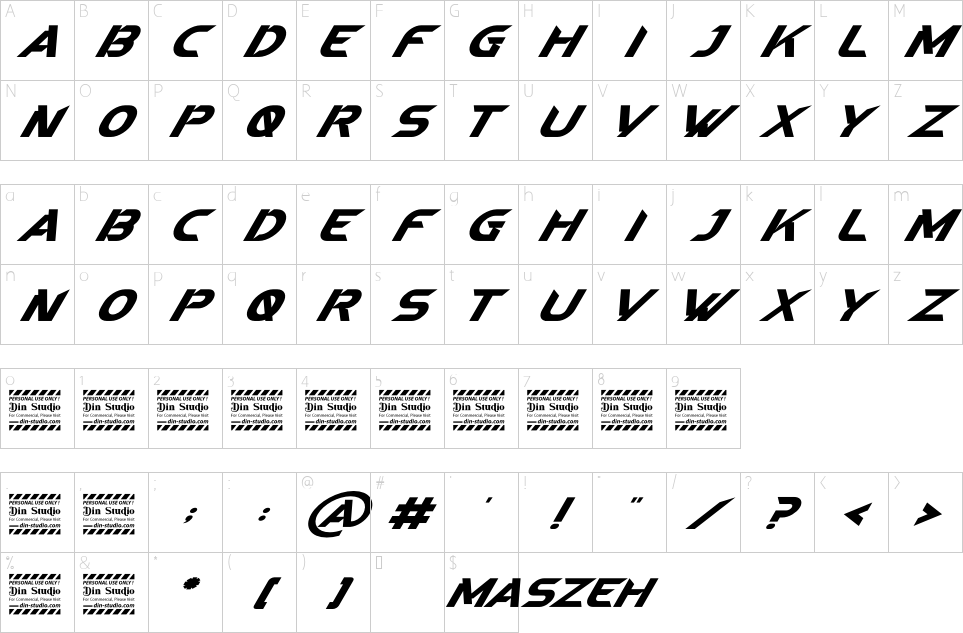
A fonte Maszeh é uma elegante escolha para designers gráficos e criadores de conteúdo que buscam uma fonte de graça e sofisticada. Desenvolvida pelo Din Studio, Maszeh foi projetada para fornecer um equilíbrio perfeito entre estética e funcionalidade. Esta fonte ganhou muitos downloads, com mais de 2,700, demonstrando sua adequação para um vasto leque de projetos. Com seu design limpo e harmonioso, Maszeh é uma opção perfeita para criar elementos de design modernos e sofisticados. Seja para assinaturas, logotipos, apresentações de PowerPoint ou até mesmo para textos de site, Maszeh oferece uma aparência que se adapta a diversos formatos de design. Se você está procurando por uma fonte de graça que se destaca, Maszeh pode ser a escolha perfeita para seu próximo projeto.